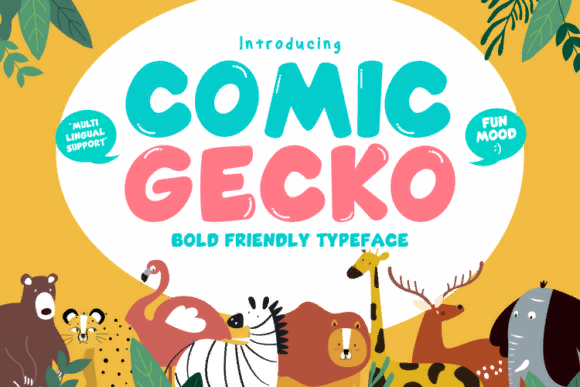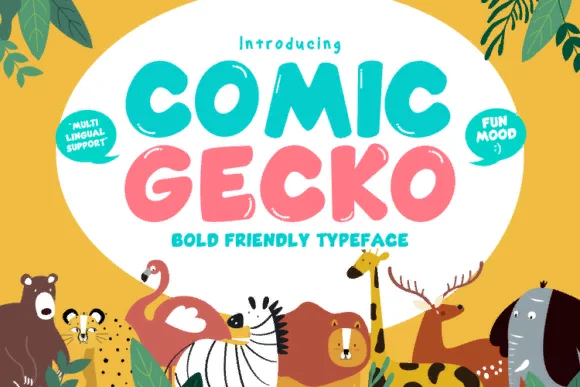
Название: Comic Gecko Font (2021)
Comic Gecko - это смелый, игривый и веселый шрифт.
Он олицетворяет радость и подлинность и прекрасно подходит для любых детских мероприятий или школьных проектов.